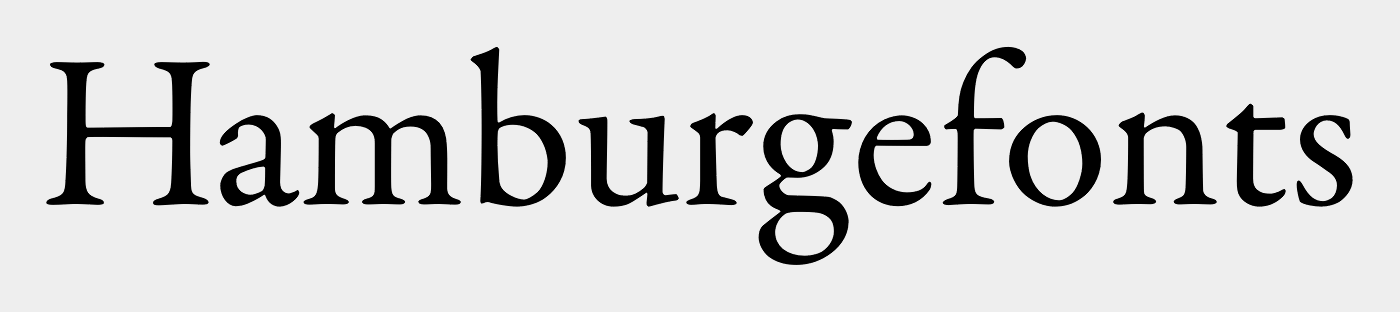
Schrift-Kombi für Projektarbeit im Bereich der Geschichtswissenschaften
gerade schreibe ich an einer Projektarbeit in Geschichte über den Völkermord an den Sinti und Roma zur Zeit des Dritten Reiches, ca. 50 Seiten.
Schon jetzt (Abgabe ist im Mai'17) mache ich mir Gedanken über das Design/Layout der Arbeit und wie viele andere hänge ich nun bei der Schriftauswahl fest...
Serifen im Fließtext, Sans für die Überschriften passen
Es sollte schon etwas exklusives sein, gerade weil wir keine strikten Vorgaben haben (lediglich "gut lesbar, neutral").
Am besten gebt ihr erstmal preisunabhängig Schriftkombi-Vorschläge ;-)
Bisherige Ideen:
Cambria / Calibri (zu langweilig)
Minion / Myriad (schon besser)
Garamond Premier Pro / Hypatia Sans Pro (gefällt mir recht gut)
Habe auch über Freight nachgedacht (https://www.welt.de/print/die_welt/literatur/article151363093/Freight-unsere-Hausmarke.html - kleiner Tipp: sucht mal im Seitenquelltext nach @font-face ;)
Und mich hast Du mit der Kombination Garamond Premier Pro und Hypatia bereits überzeugt, die verwende ich selbst häufiger.
Wir haben da mal eine Liste zusammengestellt:
Ja ich glaub auch das Thema könnte gut etwas sperrigeres vertragen. Von daher sagt mir von Deinen bisherigen Überlegungen auch Variante 3 am ehesten zu.
Ich leg mal noch ne Schippe drauf und schlage die Trivia Grotesk mit der Trivia Humanist vor. :-D
Vielleicht recherchiert man auch einfach mal nach Grafikdesign/Typografie bei Sinti und Roma. Eventuell findet man Inspirationsquellen, auf die man aufbauen kann.
Wenn Dir die Pona zusagt, könntest Du Dir auch mal die Quercus- oder Eaves-Sippe zu Gemüte führen.
Ich schwanke zwischen Arno und Garamond Premier Pro. Hängt auch ein bischen von Deinem Drucker ab, die Garamond ist sehr filigran und kann schnell zu dünn wirken. Die Arno ist da viel gutmütiger.
Hier die Reihenfolge:
Cormorant Garamond (Medium)
Garamond Premier Pro (Normal)
Baskerville (Normal)
Linux Libertine Display (Normal)
Minion Pro (Normal)
Arno Pro (Normal)
Warum Garamond Premier Pro und nicht Cormorant Garamond?
Okay, also im Fließtext Garamond Premier Pro oder Arno...
aber welche Font nimmt man dann für die Überschriften? (Kapitel und Abschnitt)
Brauchst Du ein Versal-Eszett? Dann fallen einige der genannten Schriften schon raus.
Nein, ansonsten ersetze ich durch SS.
Das Versal-Eszett ist doch noch gar nicht in die amtliche Rechtschreibung aufgenommen!?
Die selbe in 'Bolt' oder lieber so etwas wie Hypatia, Myriad, Avenir und Calibri?
Eventuell auch Le Monde Sans STD oder Oswald ?